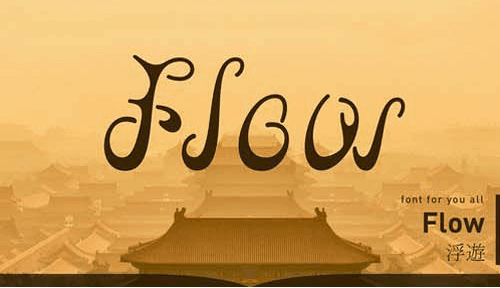
A Flow font é uma escolha perfeita para quem busca imprimir personalidade em seu design digital com leveza e elegância. Desenvolvida pelo designer Hamilton, essa fonte Playful oferece um toque descontraído que combina facilmente com qualquer estilo de layout. Suas linhas fluidas e alegres se adaptam perfeitamente para criar mensagens amigáveis e emotivas sem perder o tom profissional. Seja você criando cartões de visitas, folhetos ou até mesmo os emails que você mencionou na descrição original – Flow fornece as ferramentas certas para manter sua comunicação leve, descontraída e atrativa. A fonte é perfeita para quem procura trazer um pouco mais de vida à sua tipografia sem comprometer a essência da mensagem. Não se esqueça que usar uma fonte alegre como essa Flow pode criar uma conexão emocional imediata com seu público, tornando suas mensagens ainda mais memoráveis e eficazes.